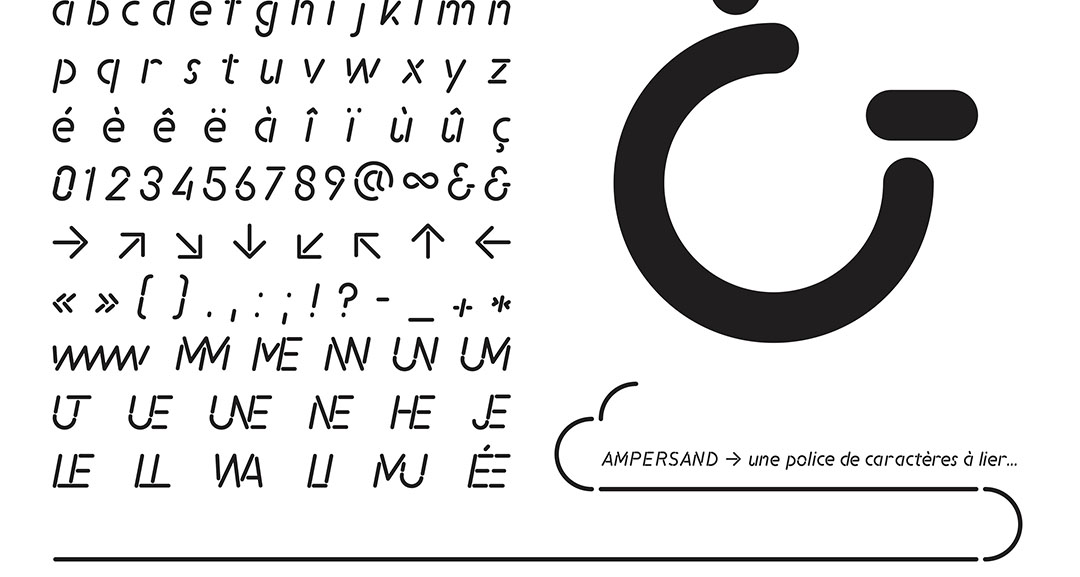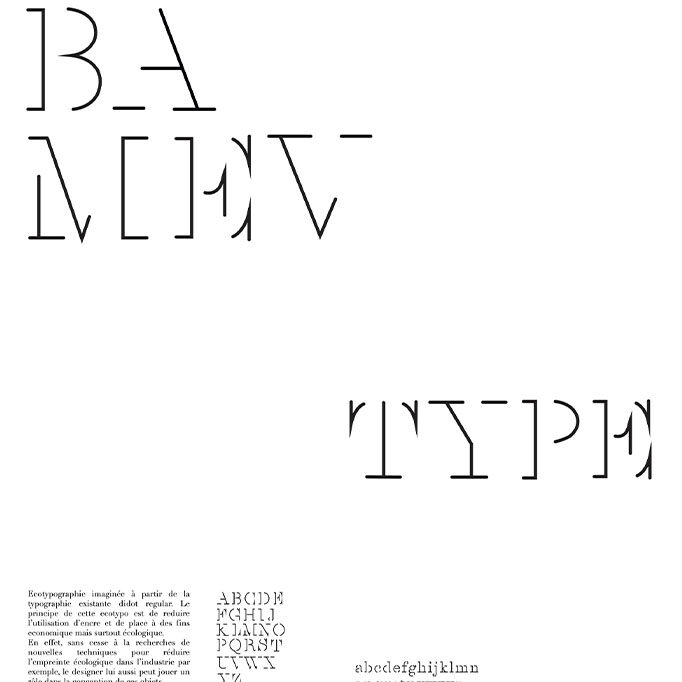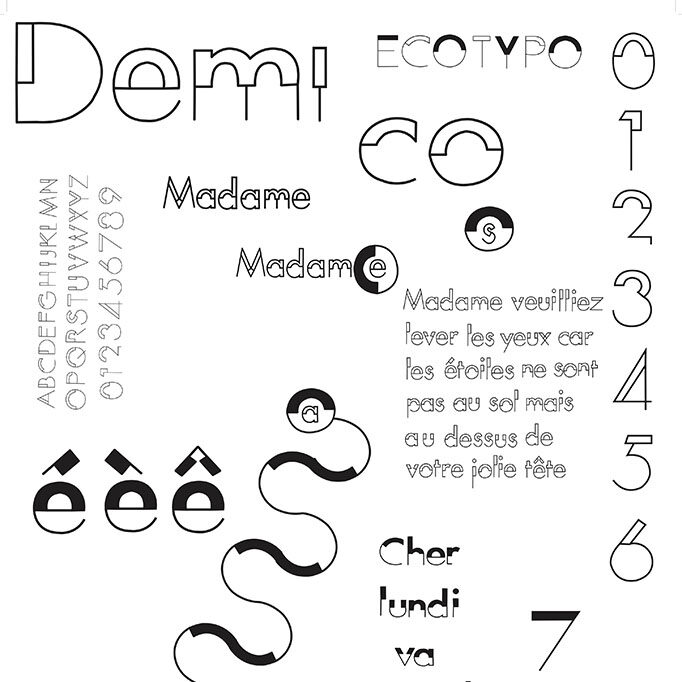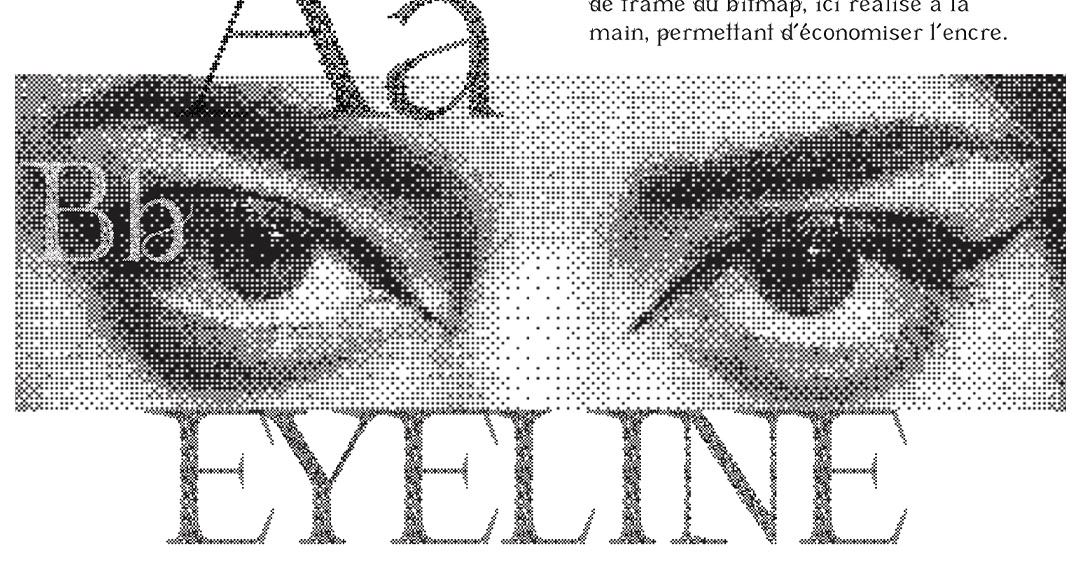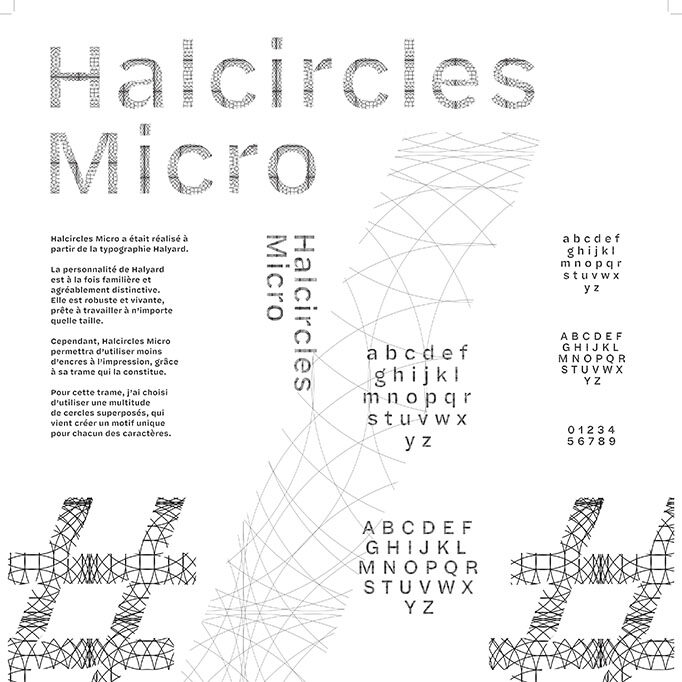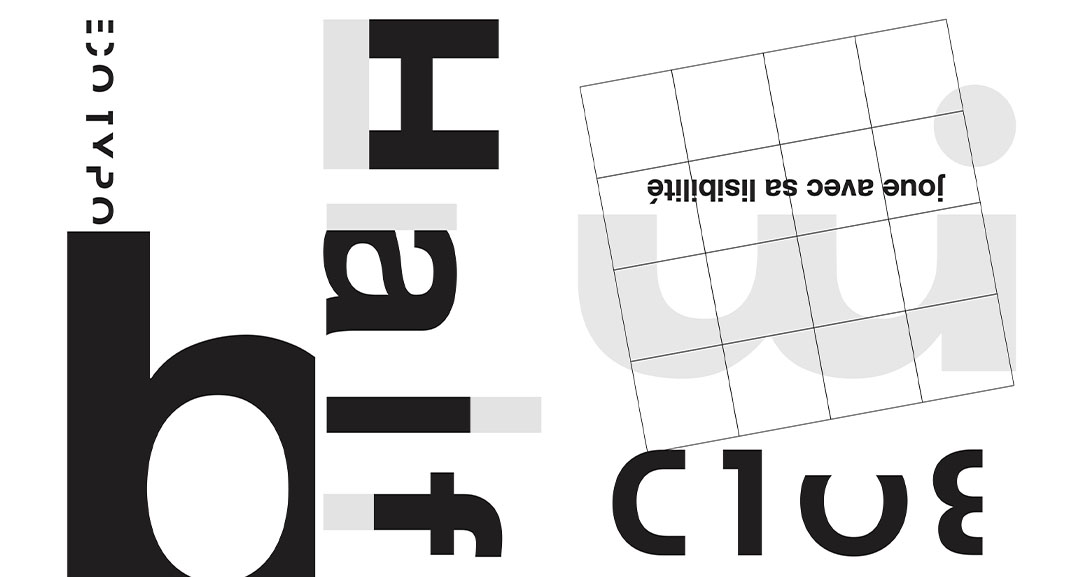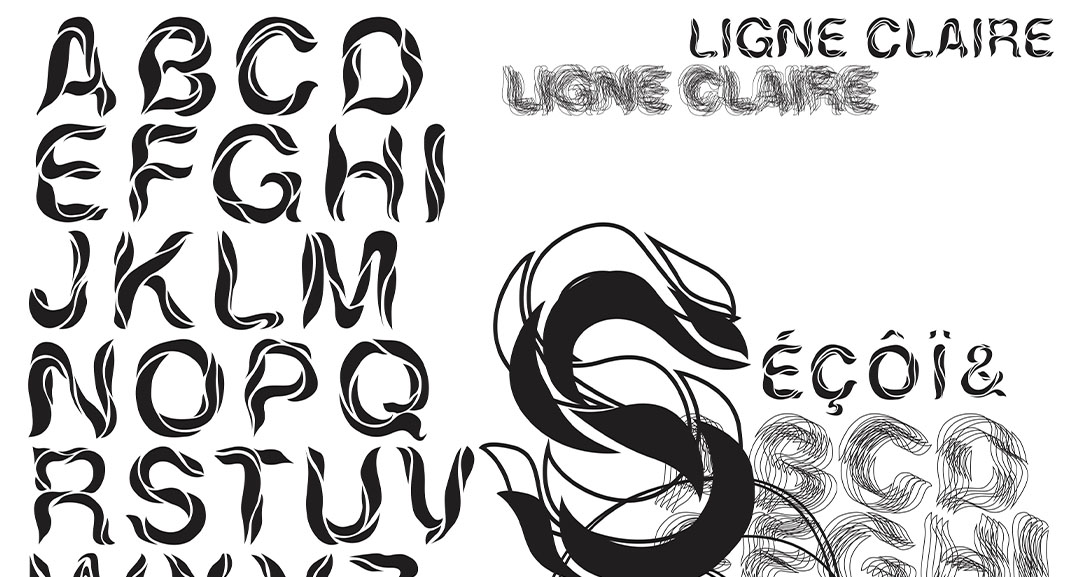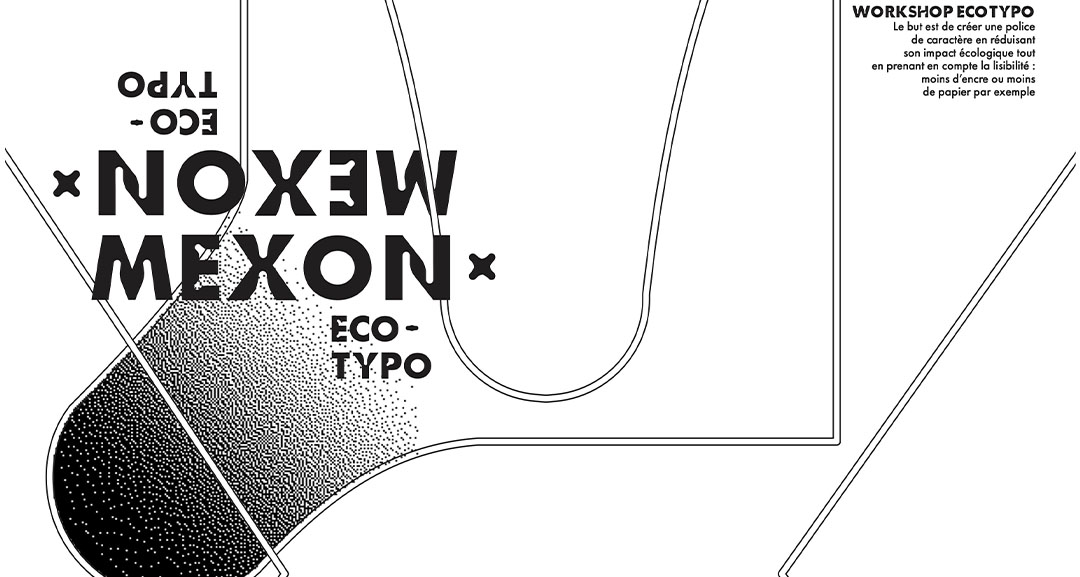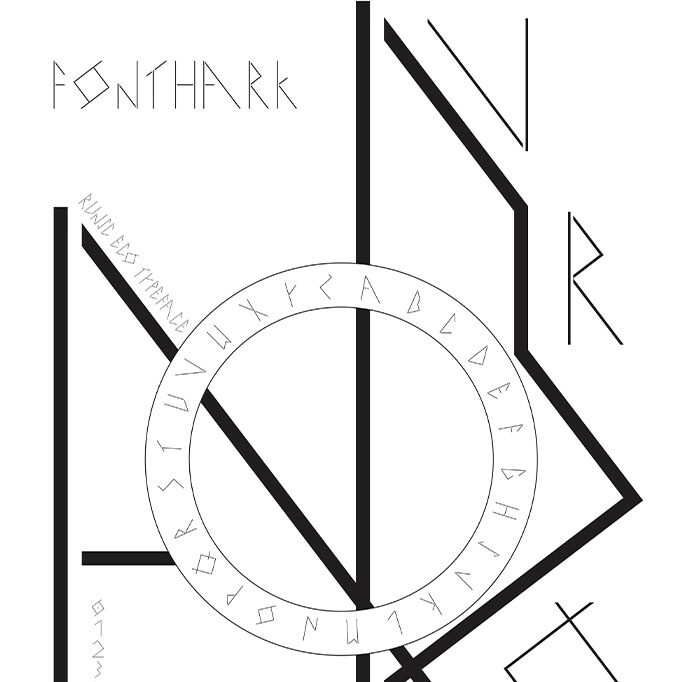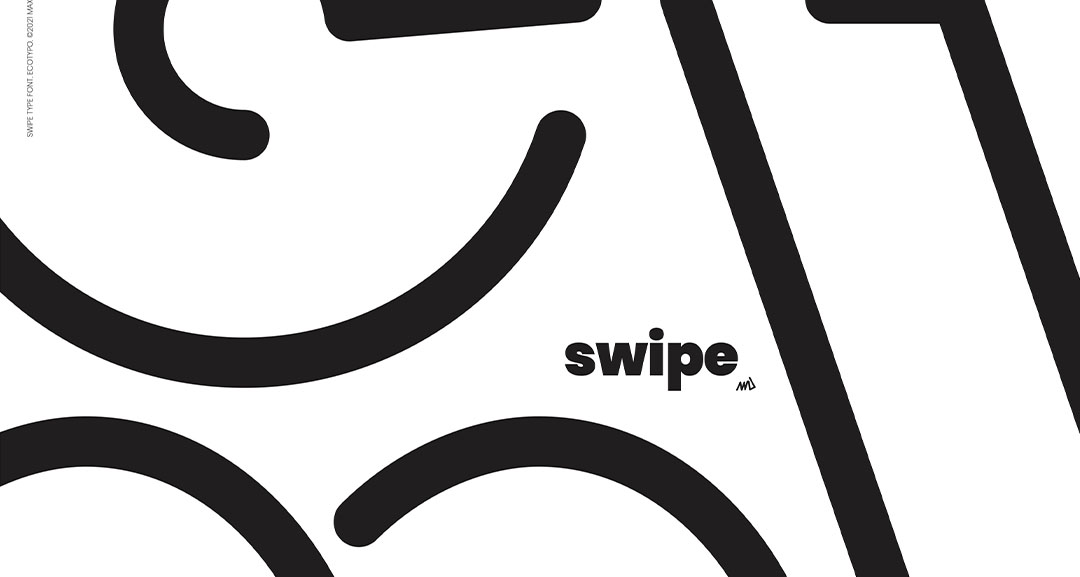
Workshop Eco-Typographie 🌿
Du 15 mars au 18 mars 2021, les étudiants en 1ère année de Mastère Design Graphique à l’ECV Lille ont participé à un Workshop Typographie avec Sébastien DELOBEL, Designer et Co-fondateur de l’Atelier Télescopique mais également Responsable pédagogique du cursus Design de l’école lilloise.
Au programme de ce Workshop Typographie : la création d’un alphabet dit « éco »… : écologique, économique.
Moins d’encre, moins de place, moins de signes, moins de papier, moins d’octets etc. Ce workshop avait pour but de concevoir une police de caractère «consommant» le moins possible, tout en respectant un certain confort de lecture.
Mais c’est quoi l’EcoTypo ? L’éco-design consiste à intégrer des critères de protection
de l’environnement dans le cycle de vie d’un service ou d’un produit. L’objectif principal est donc d’anticiper et de minimiser les impacts environnementaux négatifs.
L’éco-conception signifie donc de produire des biens et des services qui répondent aux besoins des clients en utilisant les niveaux minimaux de ressources, en ayant un impact minimal sur l’environnement et la société. Elle prend en compte l’ensemble du processus de production du produit et son cycle de vie entier, que ce soit de sa conception jusqu’à sa fin de vie, en passant par son éventuelle réutilisation et son recyclage.
Sebastien DELOBEL | Responsable pédagogique cursus DESIGNC’est important pour les étudiants, futurs designers graphiques, d’être sensibilisés aux problématiques environnementales liées au design. Une fois qu’ils ont pris conscience des enjeux, ils peuvent faire évoluer leur pratique comme par exemple utiliser moins d’encre ou des encres non polluantes, privilégier les papiers recyclés ou encore collaborer avec des prestataires locaux.